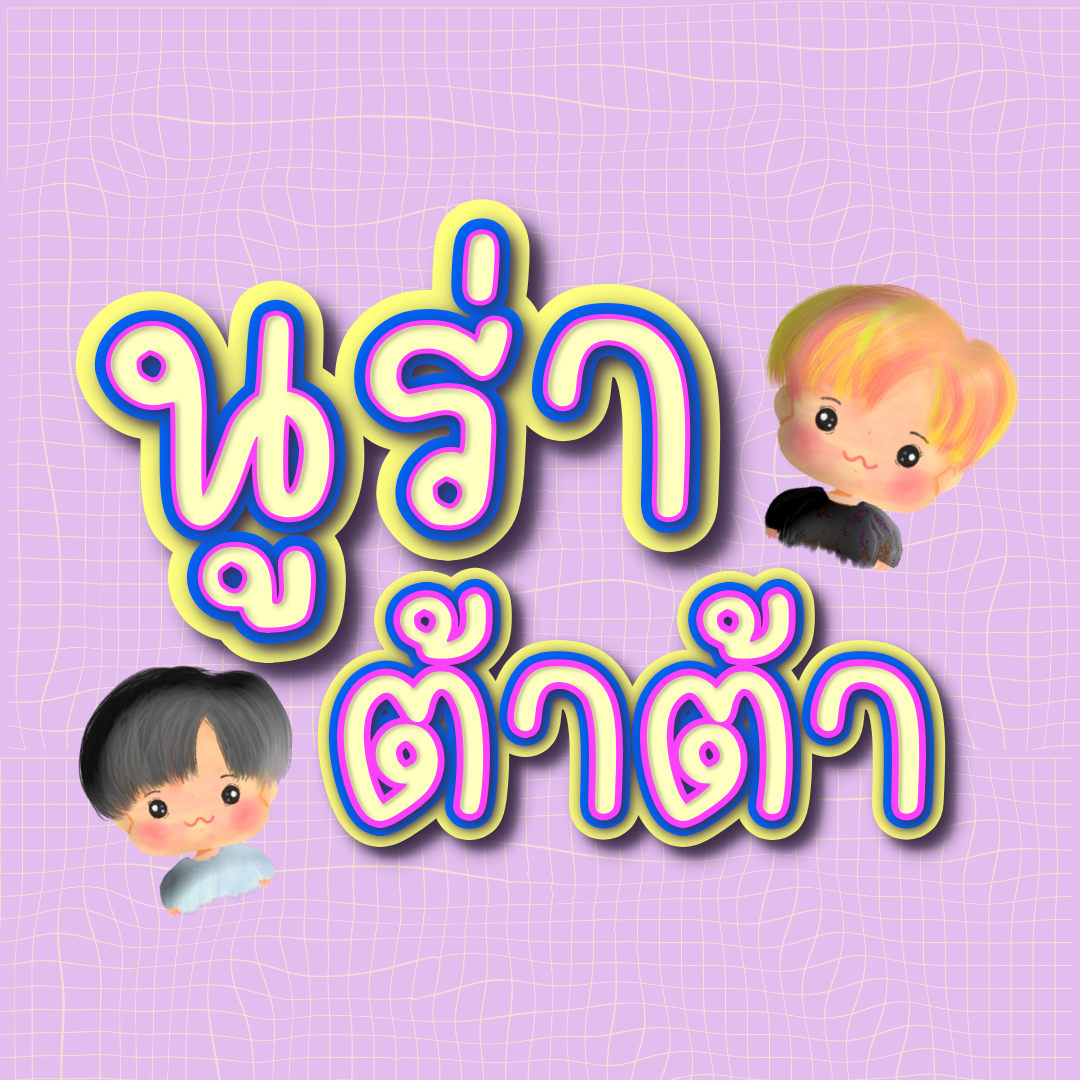
นูร่าต้าต้า (Nura tata)
ฟอนต์ลายมือตัวบาง น่ารัก หัวโตเล็กน้อย ฟอนต์มีด้วยกัน 3 น้ำหนัก คือ บาง ปกติ หนา  นูร่าราดาเปิดให้ใช้ฟรีส่วนตัว น้ำหนักบางนะคะ